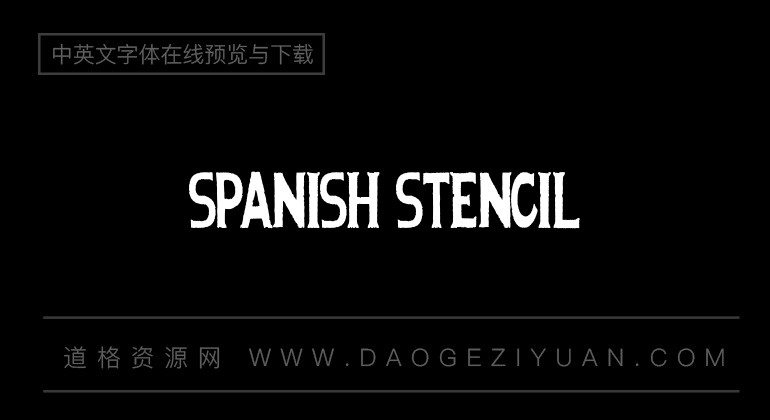
Spanish Stencil
Spanish Stencil 是一种装饰性的字体,其特点是类似于军队或警察在公共场合使用的标记字体。它具有类似于印刷品的外观和感觉,其中字母具有清晰的形状和线条。这种字体通常使用大写字母,每个字母都具有明显的特征和特征。它们通常在海报、标志、广告和其他宣传资料中使用,以吸引人们的注意力。此外,Spanish Stencil 字体还具有西班牙文化和历史的魅力,因为它类似于在西班牙战争期间使用的标记字体。如果您正在寻找一种具有历史感和装饰性的字体,Spanish Stencil 可能是一个不错的选择。
Spanish Stencil是一款非常不错的手写艺术字体,具有很好的视觉感,适合于文化类的宣传设计、商业类品牌的广告和产品包装设计以及个性化文字排版等较多场景。